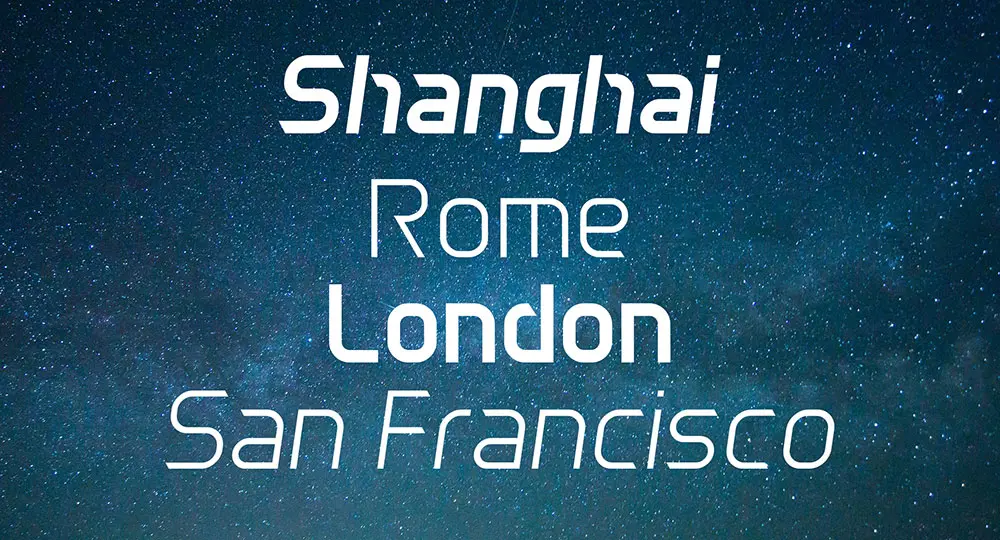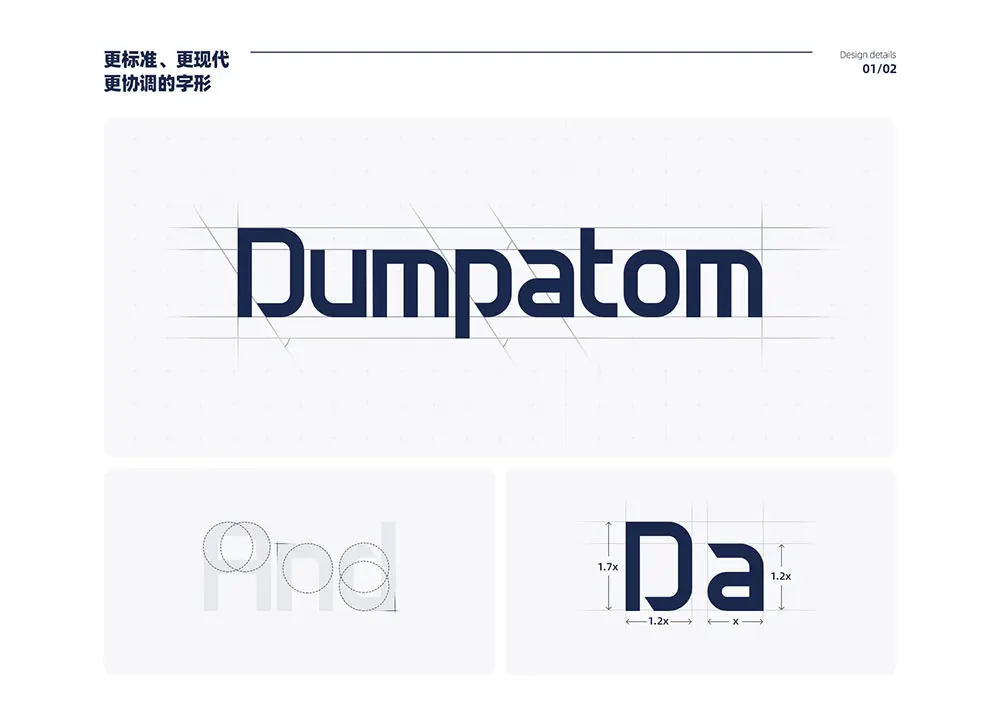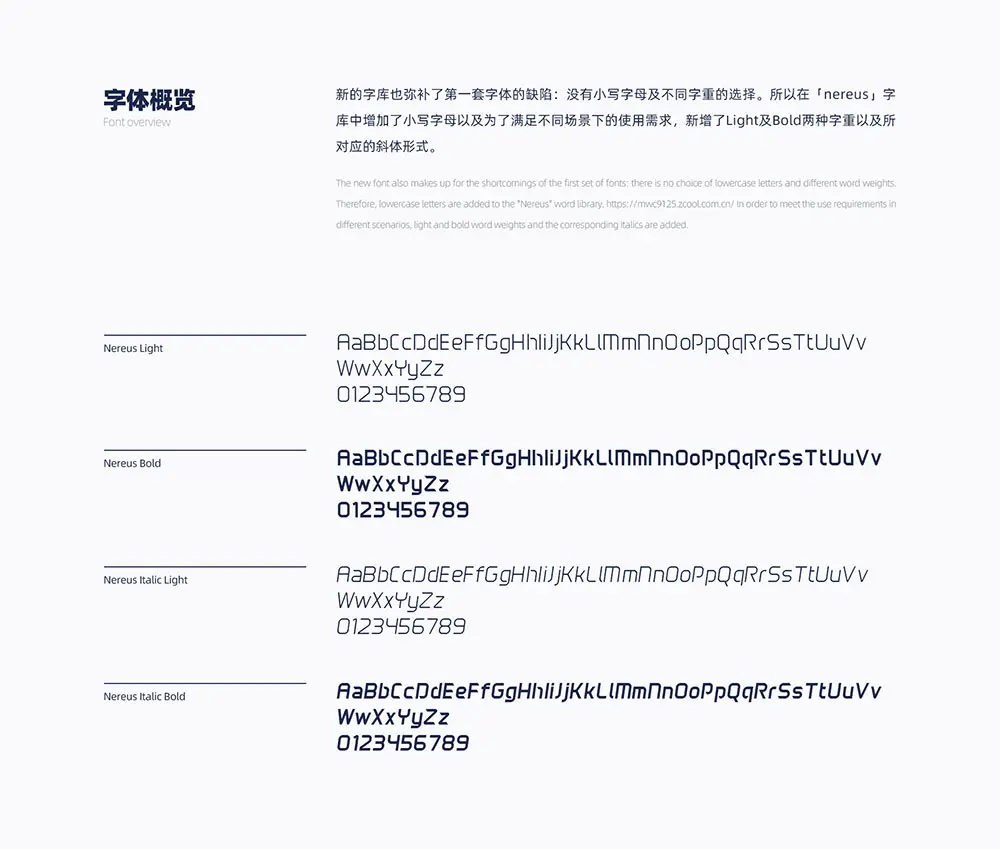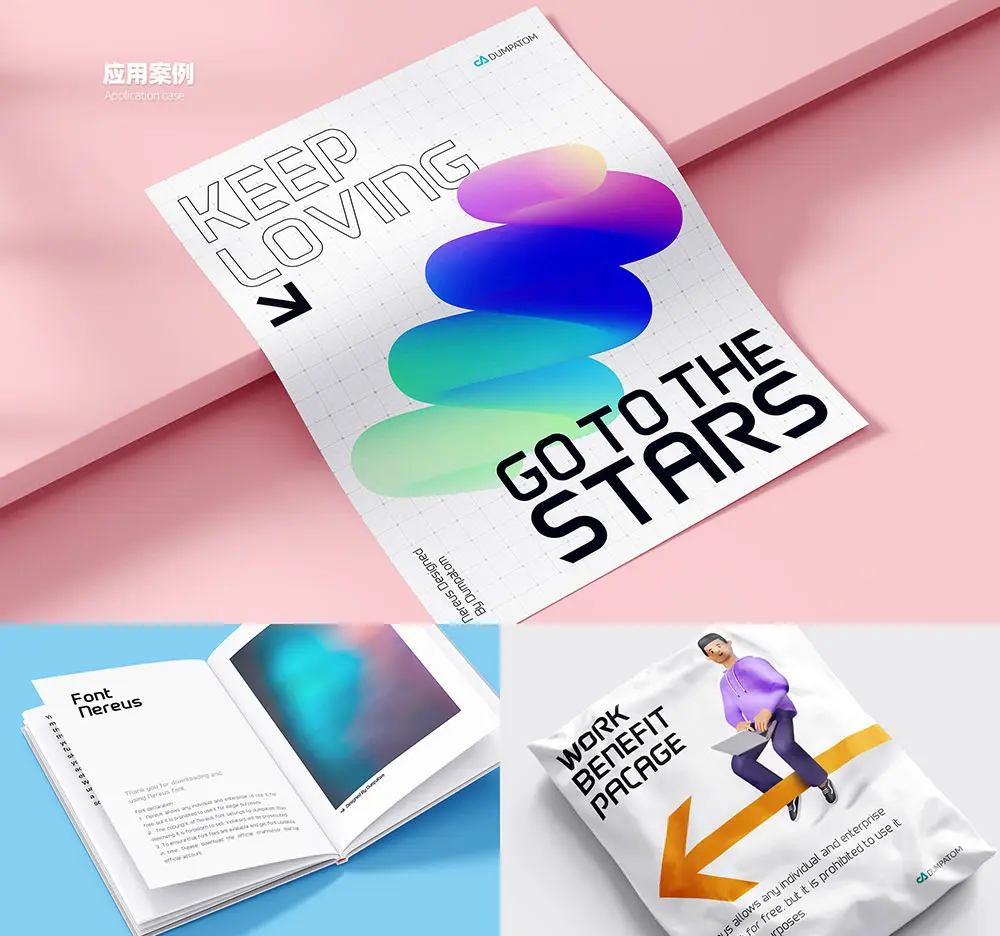
2020年9月初,在朋友的技術支持下,我於站酷平臺首發了自己設計的英文字體包「EDIX」,上線一年多的時間內,獲得了許多好評。
在一個全新的領域進行嘗試並取得了還算不錯的成績之後,我沒有停止繼續探索的腳步。在經歷了無數次的跌倒爬起後,終於能在今天提交一個滿意的答卷:完全獨立自主設計開發的第二套免費商用英文可變字體「Nereus」誕生了。—— 字體設計製作/動效設計/平面/包裝:Dumpatom毛偉丞
項目背景:Nereus涅柔斯是希臘神話中的一個海神,他值得信賴、和藹可親、公正善良。也正是被他的人格品行所觸動,所以希望能夠再設計一款字體既繼承之前字體的特性,又能在使用時更加的通用自如,最重要的是免費商用,為我所熱愛的行業貢獻自己的一點微薄之力。
設計語言探索:設計之初我構建了“Mtech”字族體系,希望能夠再後續設計的字體中能夠繼承字族中時代前進的趨勢以及現代至簡的格調,同時也希望彌補缺憾,創造一個更加通用、賦予用戶友好體驗的好字體。
設計細節:在繼承了“Mtech”字族的切角特徵以及超前的未來感和現代感之外,新的字體設計更加的規範化、統一化。在設計製作的過程中制定項目完成重要節點,在完成目標日期前克服重重阻礙,不斷的進行字體變化參數調整測試,最後憑藉一己之力成功探索出了可變字體實現技術,產出了一套通用性極強的英文字庫。